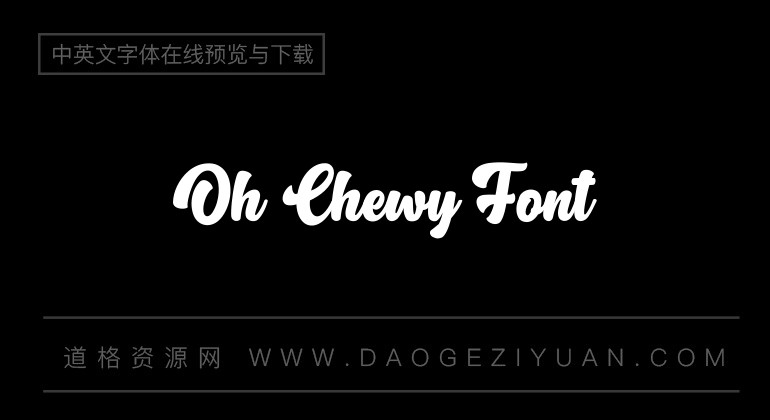
Oh Chewy Font
Oh Chewy是一种手写风格的字体,具有清晰、简单、有趣和易读的特点。它的字母形状充满了个性和活力,适合用于各种设计项目,如广告、标志、海报、包装、卡片和网站头部等。此外,Oh Chewy字体还有多种粗细度和样式,可供设计人员进行选择,并支持多种语言字符集。
Oh Chewy Font是一款非常不错的手写艺术字体,具有很好的视觉感,适合于文化类的宣传设计、商业类品牌的广告和产品包装设计以及个性化文字排版等较多场景。